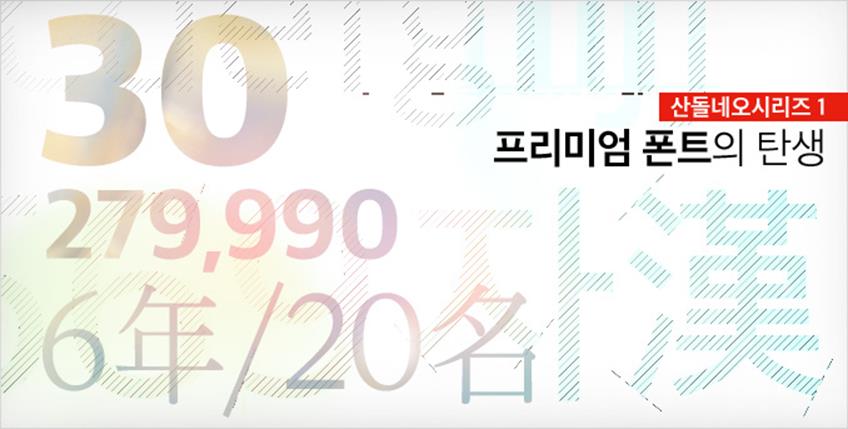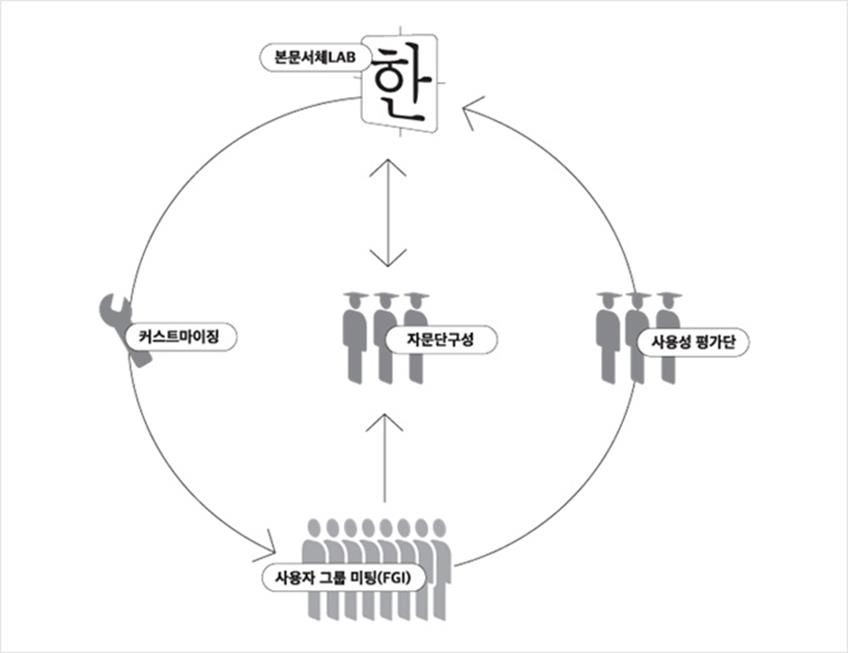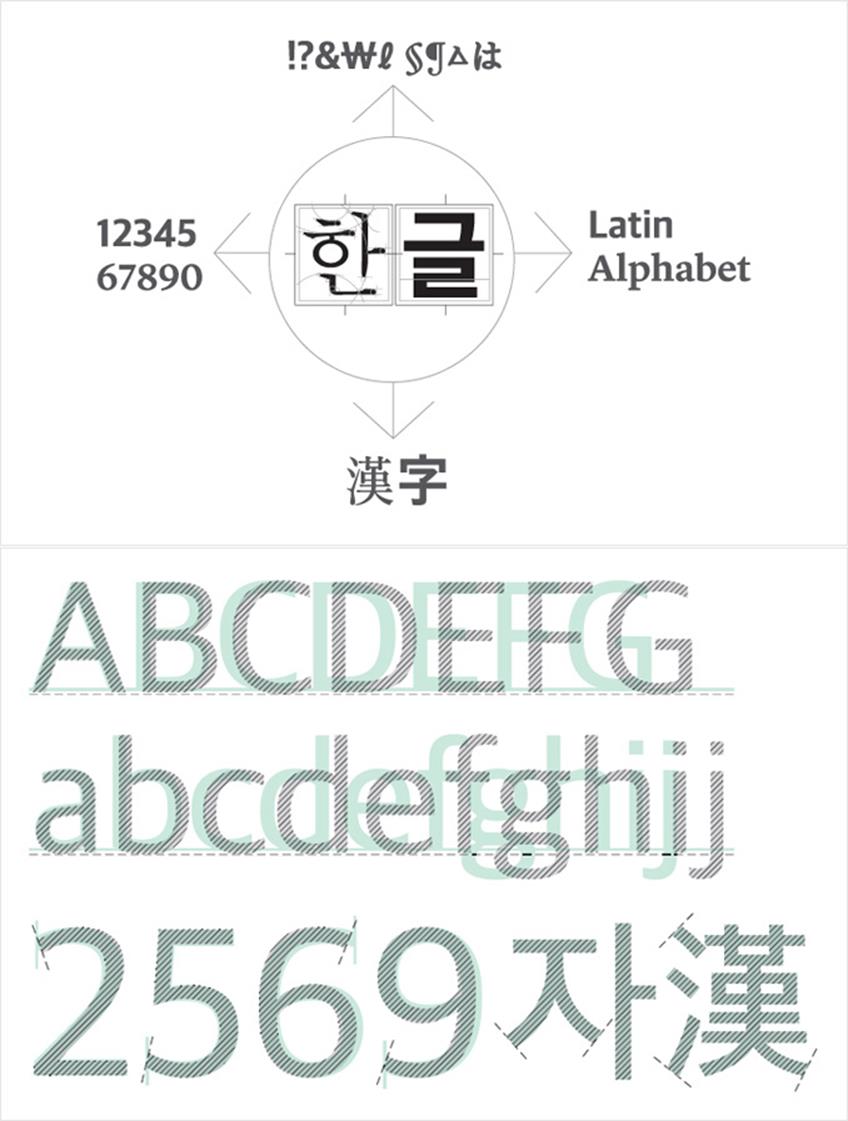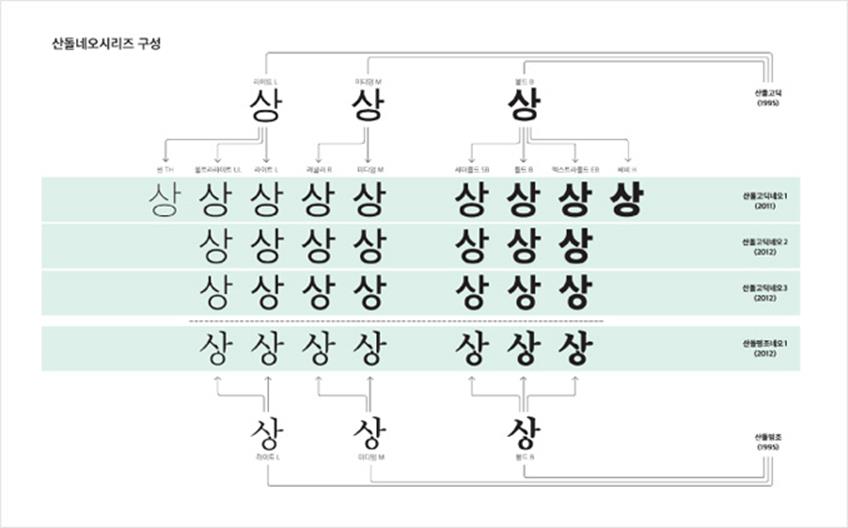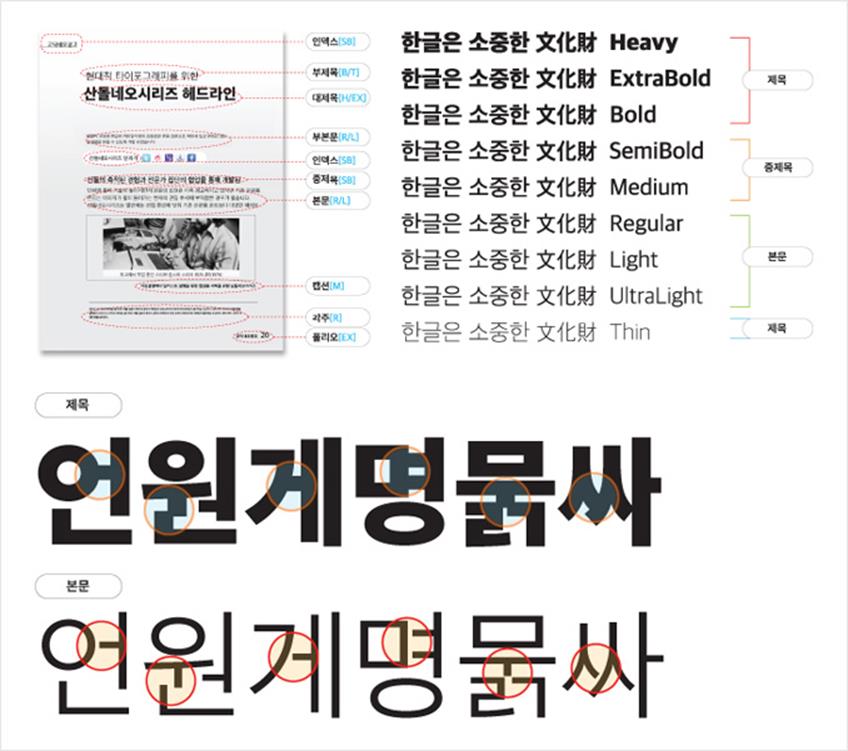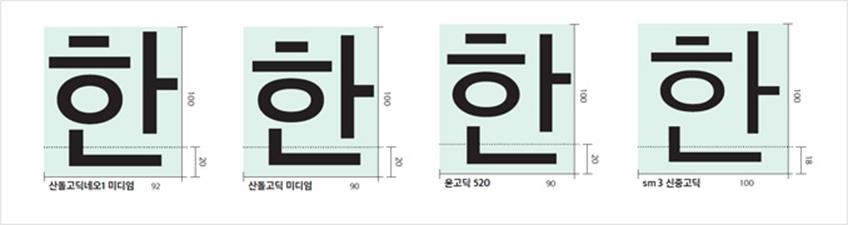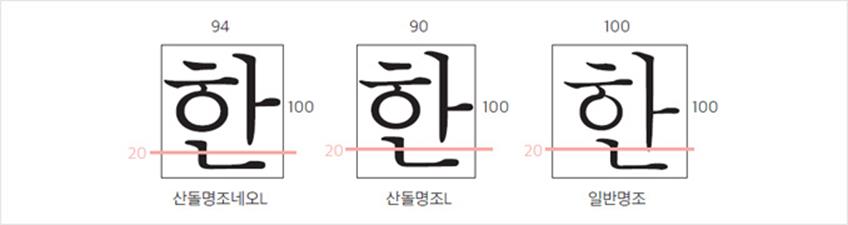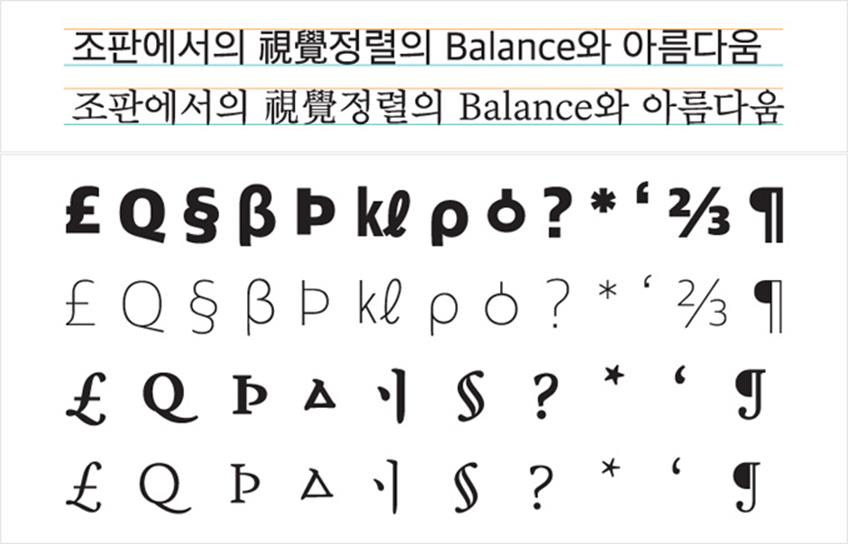
산돌네오시리즈_1.프리미엄 폰트의 탄생
산돌커뮤니케이션에서 2006년 기획을 시작해 6년에 걸쳐 제작한 산돌네오시리즈를 정식으로 출시했다. 본문 서체 디자인을 위해 오랜 시간 연구하고 노력한 산돌의 오랜 결실이 이뤄진 것. 산돌의 프리미엄 폰트라는 기치를 내걸고 그 간의 기술과 경험을 모두 담아낸 산돌네오시리즈는 고딕과 명조를 포함해 총 30여 종에 이르는 패밀리를 이루고 있다. 앞으로 산돌네오시리에 대한 전반적인 소개를 시작으로 고딕네오와 명조네오의 특징, 제작에 참여한 디자이너 인터뷰, 네오시리즈를 사용해본 디자이너들의 리뷰를 정리해 4회에 걸쳐 순차적으로 소개한다.
산돌네오시리즈의 가장 큰 특징은 네 가지로 요약된다. 사용자를 최우선으로 생각하고 사용자의 참여로 이루어진 디자인이라는 점과 한글을 가장 중심에 두고 다른 문자 군과 조화를 이루어낸 최초의 한글 서체라는 점. 그리고 다양한 패밀리로 사용자에게 선택의 폭을 넓혀 주고, 디지털 환경에 맞게 설계되어 최신 환경에 적용하기 수월하다는 점이 바로 그것이다.
사용자 중심
한글 서체 개발은 개발 기간도 길고 디자인 완성도를 높이는 일도 쉽지 않아 소비자의 요구를 따라잡기 어려운 분야 중 하나다. 그래서 그 동안 한글 서체는 대부분 공급자 위주로 개발해 제품을 출시해 온 것이 사실이다. 결국 사용자들은 서체개발회사에서 제품을 내놓으면 불편해도 어쩔 수 없이 사용할 수밖에 없었다. 반면, 산돌에서 기획하고 개발한 네오시리즈는 기존의 서체 개발 개념을 뒤집어 엎은 보기 드문 사례다. 편집 및 분야별 디자이너의 의견에 귀를 기울이고 사용자 그룹 인터뷰를 통해 문제점, 불편한 점, 제안, 아이디어 등을 수집해 반영한 것이다. 또한 전문 자문단을 구성해 한글 서체에 대한 다양한 의견과 해결책을 공유하고, 출시 직전의 산돌네오시리즈에 대한 감수와 자문을 의뢰하기도 했다. 이를 위해 네오시리즈 프로젝트를 위한 전담연구제작팀이 운영되기도 했다. 다양한 사용자에게 맞춰 커스트마이징이 가능하도록 서체 구성 자체를 각각의 모듈로 구분한 것 또한 특징이다.
산돌은 네오시리즈 프로젝트를 위한 전담연구제작팀을 구성해 일반 사용자, 기업, 전문 디자이너들의 의견을 수렴해 반영했다.
한글디자인 중심
근대 인쇄 문화와 활자 디자인은 외국의 영향을 받아 주체성을 가질 수 없었고 디지털 환경의 빠른 변화 탓에 한글 서체 디자인은 오랜 시간 외면 받아온 것이 사실이다. 아직도 여러 애플리케이션은 한글을 타이포그래피의 부가기능 정도로 치부하고 있다. 이 같은 안타까운 상황에서 산돌네오시리즈 프로젝트는 무엇보다 한글디자인을 중심에 두고 개발이 진행되었다. 한글디자인 컨셉트에 맞춰 라틴알파벳을 선택해 수정 보완하고 한글에 맞춰 한자를 만든 것이다. 부가 기능과 기타 기호들도 한글을 위해 만들어졌고 한글의 품위를 손상하지 않도록 국적 없이 떠돌아다니는 문자들을 함부로 접목하지 않았다.
라틴 알파벳을 비롯한 숫자, 문장부호 등 글립들을 개발하는 최선의 방법은 그 문법과 조형 원칙을 정확하게 이해하는 라틴 문자권의 디자이너와 공동 개발하는 것이다. 산돌고딕네오1은 차선에서 최선을 찾았다. 즉 기존의 라틴 알파벳 중 한글의 구조와 골격에 가장 어울리는 글자체를 선정했다. 그렇게 여러 후보들을 놓고 신중한 테스트를 거친 끝에, 산돌고딕네오1에 가장 어울리는 라틴 글자체로 가디언산스 헤드라인(Guardian Sans Headline)을 택했다. 산돌고딕네오1은 라틴 알파벳 글자체를 글립으로 사용하기 위해 정식으로 저작권을 구입한 국내 유일의 사례이다. 라틴 글립 디자인 저작권 구입 후에는 한글 조판 환경의 특수성에 따라 불가피하게 수정이 이루어져야 했다. 수정 버전은 원저작자와의 합의 하에 산돌가디언산스(Sandoll Guardian Sans)라는 이름이 부여되었다. 가디언산스 본래 성격은 최대한 유지하되, 변경 사항들은 한글과 서로 어울리도록 하는 목적으로만 제한되었다. 수정 내용은 모두 오리지널 버전의 디자이너인 크리스챤 슈바르츠의 최종 감수를 거쳐 확정되었다. (내용출처. 산돌고딕네오1 견본집, 20쪽)
입체적 편집을 위한 다양한 패밀리
다양하고 정교한 편집을 위해서는 각각의 목적과 기능에 맞춰 세분화된 패밀리가 필요하다. 웨이트의 부족함은 그 동안 산돌 서체 선택을 꺼리는 이유 중 하나로 지적되기도 했다. 산돌네오시리즈에서는 웨이트 변화에 의한 1차 패밀리를 넘어 다양한 목적과 기능을 가질 수 있는 확대된 개념의 패밀리가 구상되었다. 한글 자소의 조합구성에 변화를 주어 안정적이고 클래식한 이미지와 젊고 리드미컬한 이미지에 어울리는 패밀리를 갖추게 된 것이다. 또한 웨이트 패밀리간에도 목적과 용도에 맞도록 설계해 기능성이 향상되었다. 본문용은 가독성에 중점을 두어 자소 간에도 또렷하게 구분되며 문장을 이루었을 때도 자연스러운 시각적 체계를 갖추도록 하고, 제목용은 주목성에 중점을 두어 짧은 문장이 하나의 덩어리가 되어 시선을 잡아 끌 수 있도록 했다.
산돌네오시리즈는 전체 4서체 30종으로 구성되었고, 고딕네오1은 9종, 고딕네오2와 고딕네오3, 명조네오1은 각각 7종의 웨이트로 이루어져 있다.
다양한 웨이트를 제공하는 이유는 예민한 편집 디자이너들의 까다로운 요구에 부응하기 위해서이다. 동일한 텍스트라도 선호도에 따라 레귤러를 중심으로 활용하면 좀더 차분하고 밝고 가벼운 색채감을, 세미볼드를 중심으로 활용하면 좀더 힘있고 단단한 색채감을 얻게 된다. 한편, 한글은 각 음절의 글자 당 획수가 라틴 알파벳보다 현저하게 많다. 그러므로 고딕체를 골격으로 헤어라인(Hairline)이나 블랙(Black)과 같은 극단적인 웨이트를 표현하기에는 무리가 있고, 웨이트 간 무게감의 차이도 그만큼 뚜렷하지는 않다. 따라서 산돌고딕네오1의 웨이트들은 극적인 표현력보다는 정교한 조율 능력에 초점이 맞추어져 있다. 그 동안 인쇄기와 출력기 기술은 점차 정교해져왔고, 종이의 질이나 성격도 다양해졌다. 이러한 환경의 변화에 기존 본문 글자체들은 잘 부응해오지 못했다. 종이마다 번짐의 정도가 다르니, 유광이나 무광 코팅이 된 종이에 인쇄된 미디엄은, 코팅되지 않은 종이에 인쇄된 레귤러와 비슷하게 보이게 된다. 이렇듯 선택한 종이의 성격, 혹은 인쇄방식에 따른 미세한 차이를 고려하여 웨이트를 서로 대체해서 적용할 수 있다. (내용출처. 산돌고딕네오1 견본집, 10쪽)
디지털 타이포그래피에 맞춘 설계
산돌네오시리즈는 새로운 타이포그래피 환경에 맞게 가로쓰기 전용으로 설계되었다. 디지털 기기와 디스플레이 기술에 최적화 되도록 원도제작에서부터 응용 테스트까지 최신환경을 고려해 제작되었다. 우선 산돌고딕이 지니고 있던 가로쓰기와 적정 자간을 이어받아 현대 타이포그래피가 요구하는 글자 폭에 일반고딕 보다 비교적 왜소해 보였던 약점들을 보완했다. 특정한 조절 값을 입력하지 않아도 미려한 조판이 가능해진 것이다. 또한, 조판 조절 값 없이 사용해도 자간, 자폭, 띄어쓰기가 최적화되었고, 합성글꼴을 사용하지 않고도 세련된 정렬과 조화가 가능해진 것이 특징이다.
산돌고딕네오의 경우 글자 폭은 sm3신중고딕의 경우처럼 100%의 전각이 아니라, 92%로 장평을 좁게 설계했다. 폭이 좁게 설계된 다른 고딕체의 예로는 90%의 기존 산돌고딕, 90%의 윤고딕 500대 등이 있다. 아랫기준선(baseline) 위치는 다른 고딕체들의 경우와 대동소이하다. 모듈 내부 형태적 특성에 관해서는, 주어진 공간을 시원하게 채워 기존 산돌고딕처럼 같은 포인트의 크기에서 상대적으로 왜소해 보였던 성격을 극복하고자 했다. 또한 전체 글자폭을 차지하는 사각형 내부, 글자 형태 양끝으로 남는 하얀 공간인 사이드베어링(sidebearing)을 세심하게 조절하여, 조판시 짜임새 있는 자간 값을 갖도록 했다. 산돌고딕네오는 탈네모가 아닌 네모틀의 한글 글자체이지만, 초성, 중성, 종성의 자소들이 네모틀 내부에서 조금 더 자유로워진 형태를 갖추고 있다. 모듈 내부의 검은 글자와 흰 공간은 가지런하게 안배되도록 했으며 종합적으로 기존 산돌고딕처럼 고전적이기보다는 긴장감과 탄력이 넘치는 현대적인 이미지를 담을 수 있게 되었다. (내용출처. 산돌고딕네오1 견본집, 16쪽)
한편, 산돌명조네오의 경우 기존 산돌명조가 보여주는 활자의 자면 보다 크기를 크게 하여 현대적 본문편집에 맞는 안정감을 갖고, 많은 내용의 문자 수에도 행과 글자 사이가 명료하게 살아나도록 공간 체계가 설계되었다. 자소 크기와 속공간을 확대하여 현대적 가로쓰기 조판에서의 판독성을 높이고, 정밀한 조판 조절 없이도 미려한 타이포그래피 효과를 쉽게 얻도록 한 것이다. 또한 원도제작에 있어 디지털 작도법에 맞춰 정확하게 디자인 함으로써 디지털 디스플레이 환경에서 서체가 표현될 때 왜곡 없이 균일하고 또렷하게 보이도록 했다. 더불어 네오시리즈에서만 볼 수 있는 아름답고 세련된 특수기호 문자들을 사용할 수 있도록 했다.